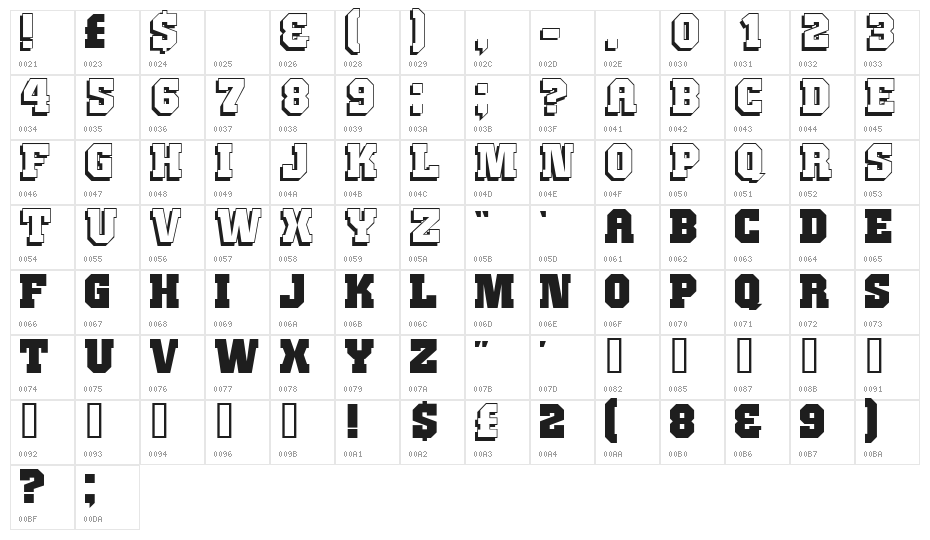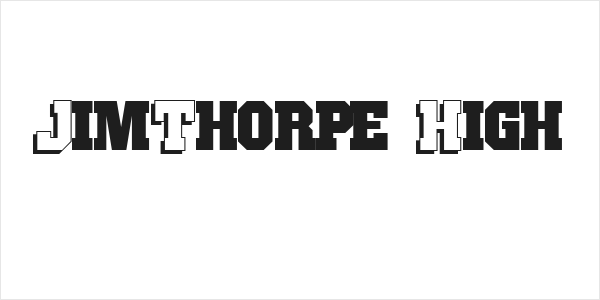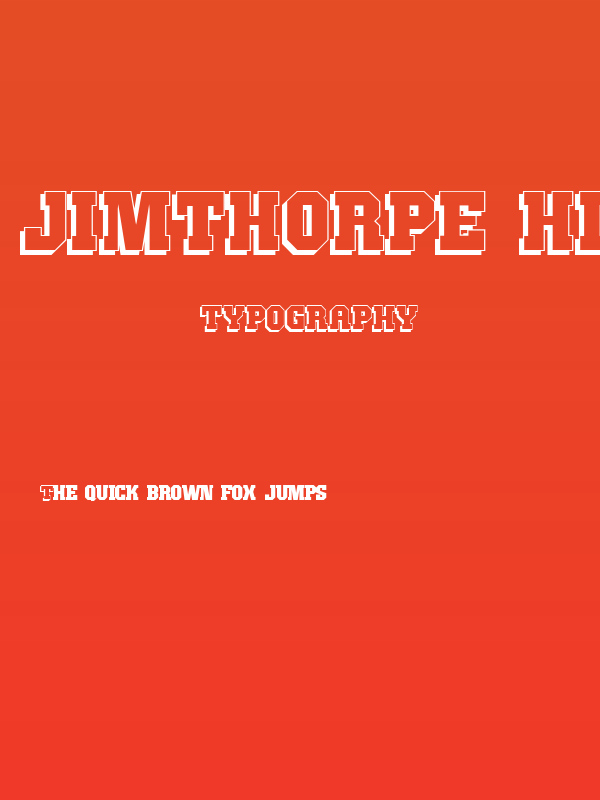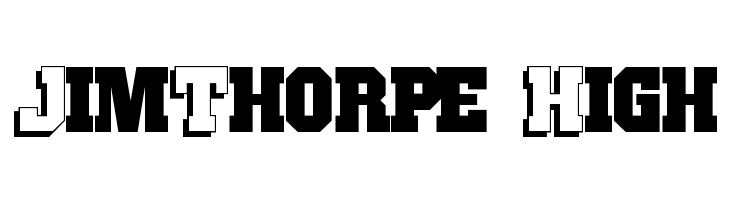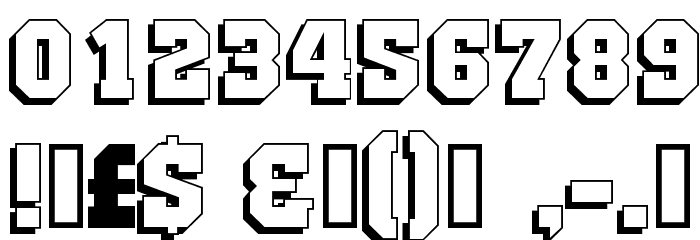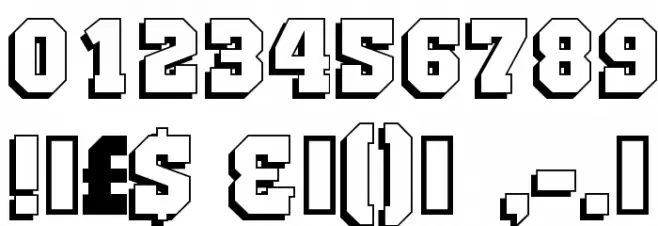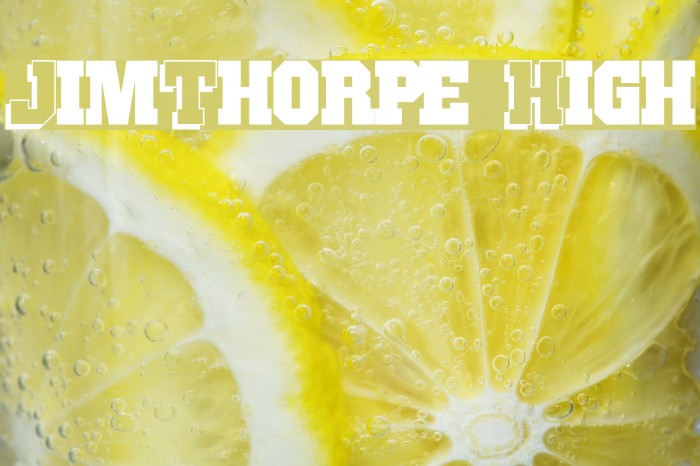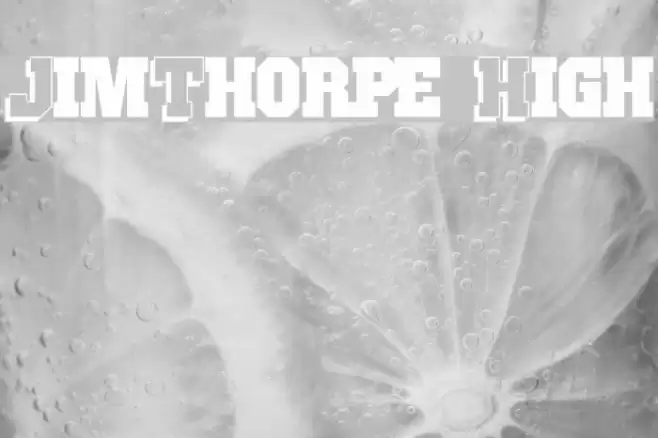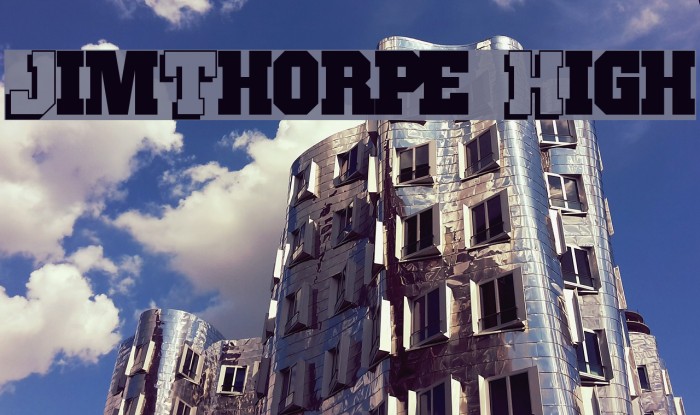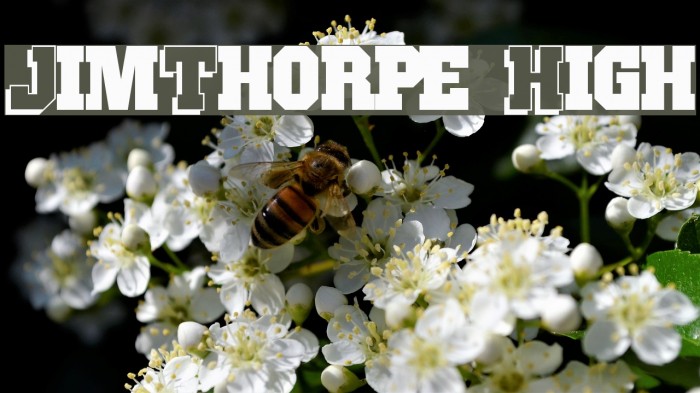
JimThorpe High Font
✎ Old fashioned
| Рекомендуемые проекты | Ideal for sports branding, posters, headlines, and any project needing a bold, impactful typeface. |